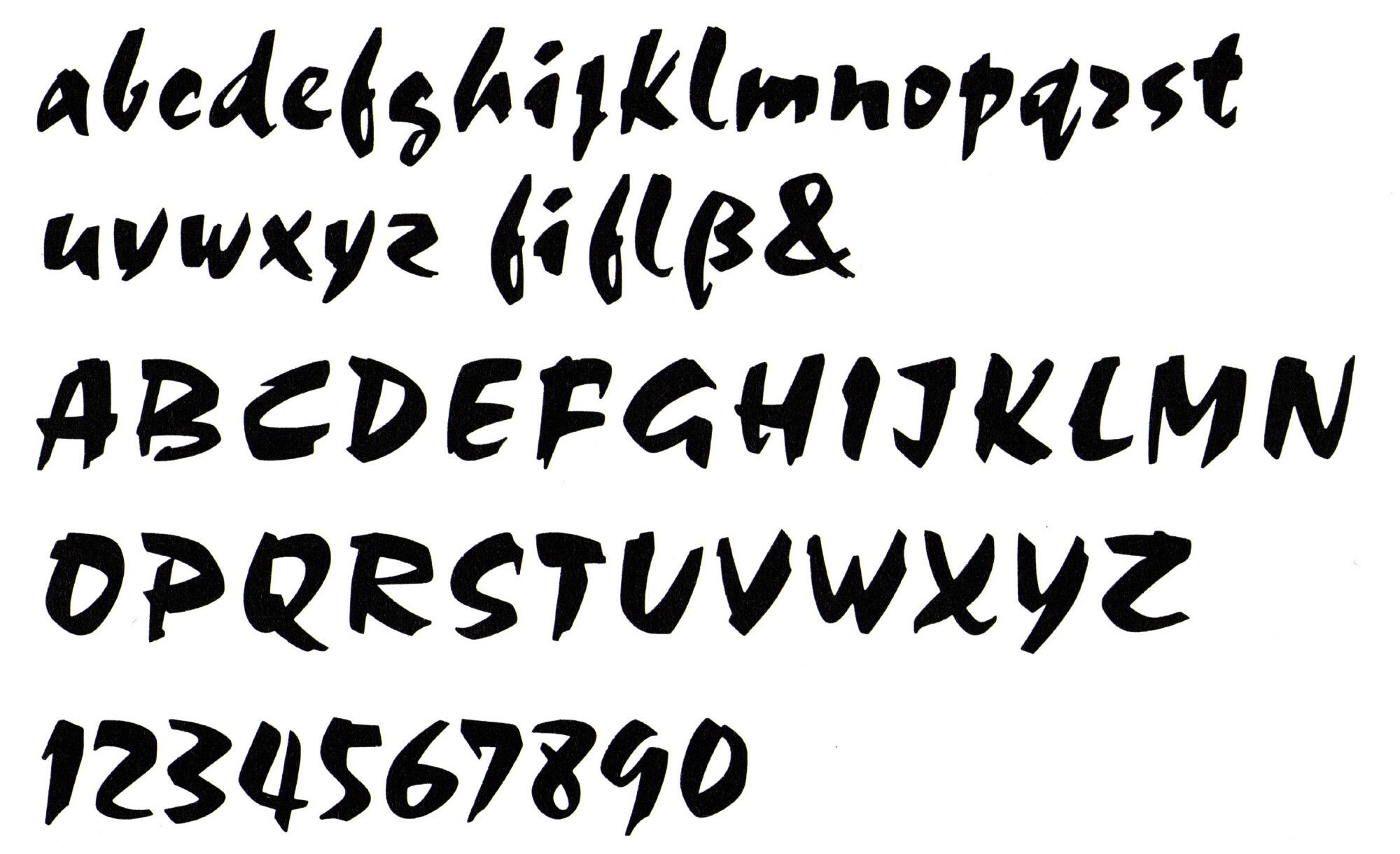
- 1955
- Antiqua dekorativ
Nach dem großen Erfolg der Mistral (1953) wollte man diese Schrift bei der Fonderie Olive noch weiter ausbauen. Die Choc war ursprünglich als fette und besonders raue Version der Mistral geplant, aber man entfernte sich in den Entwürfen immer weiter von dieser Idee und entwickelte die Choc schließlich als eine völlig eigenständige, unverbundene Schreibschrift mit deutlichem Pinselduktus.